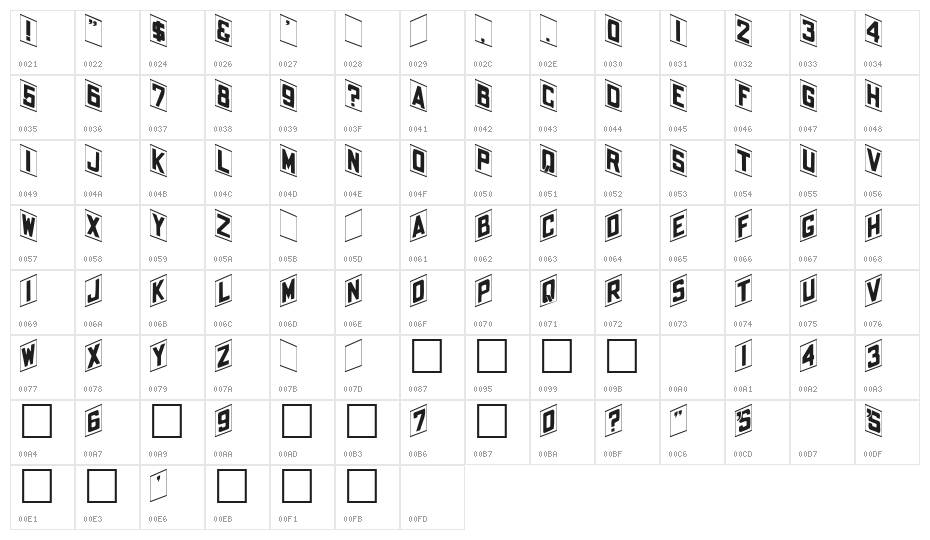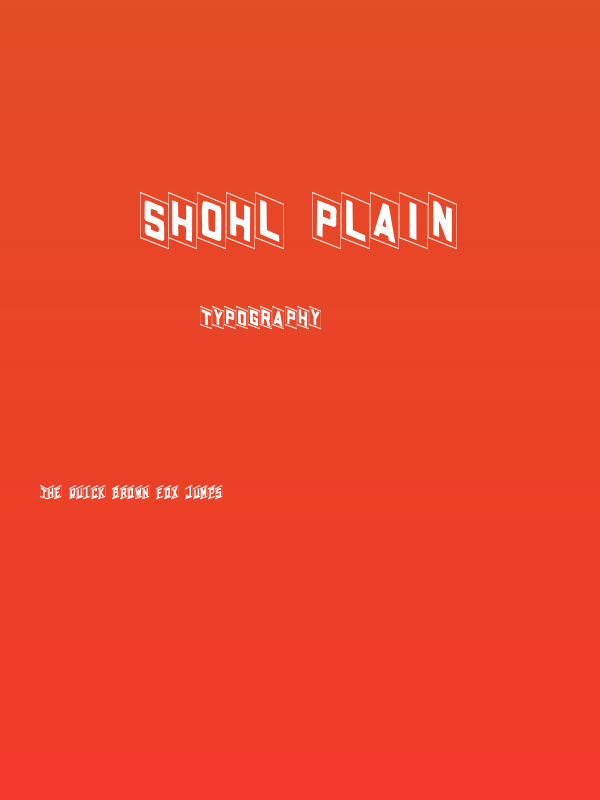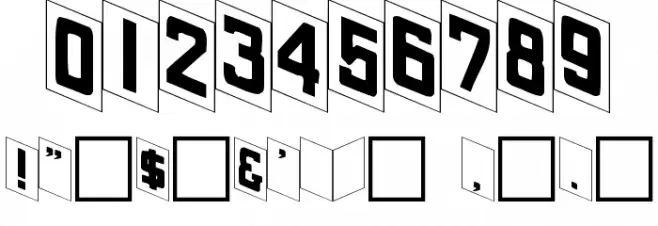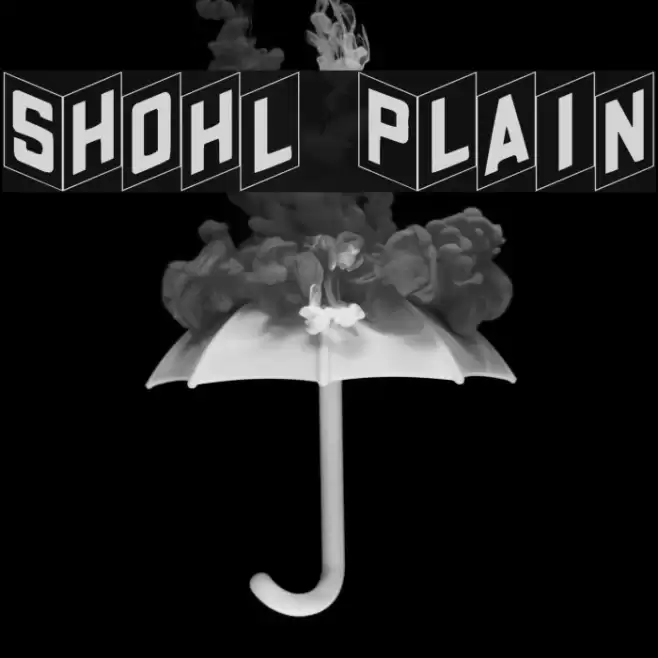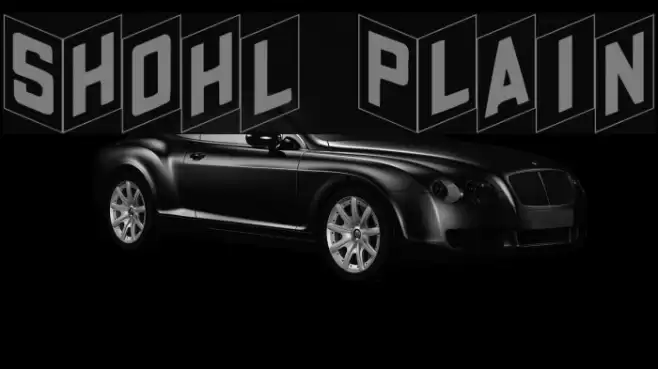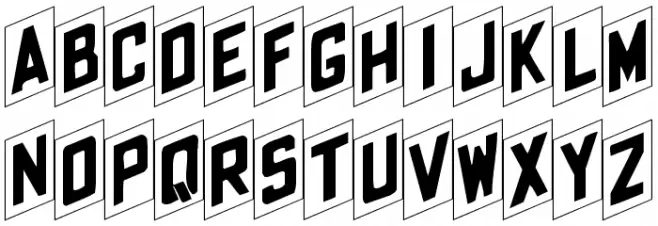
Shohl Plain Font
| Рекомендуемые проекты | This font is perfect for projects that require a strong visual impact, such as posters, logos, and branding materials. Its unique style makes it suitable for retro-themed designs, video game graphics, and any creative work that benefits from a bold, eye-c |